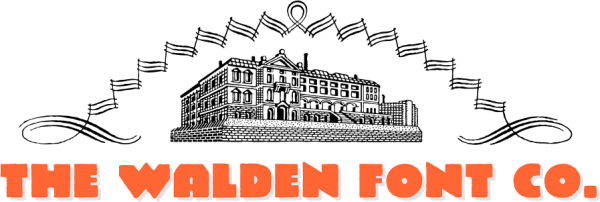
Walden Font Co.
• Land: Vereinigte Staaten
• Ort: Winchester, Massachusetts
• Gegründet: 1995
Die Walden Font Co. begann als Steckenpferd von Oliver Weiß. 1990 in die USA ausgewandert, entwickelte er zuerst einfache, aber praktische »Design Kits« nach historischen Themen. Später stand das Wiedererwecken vergessener Schriften im Blickpunkt.